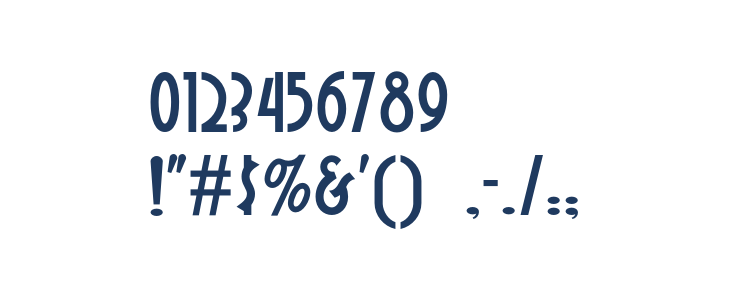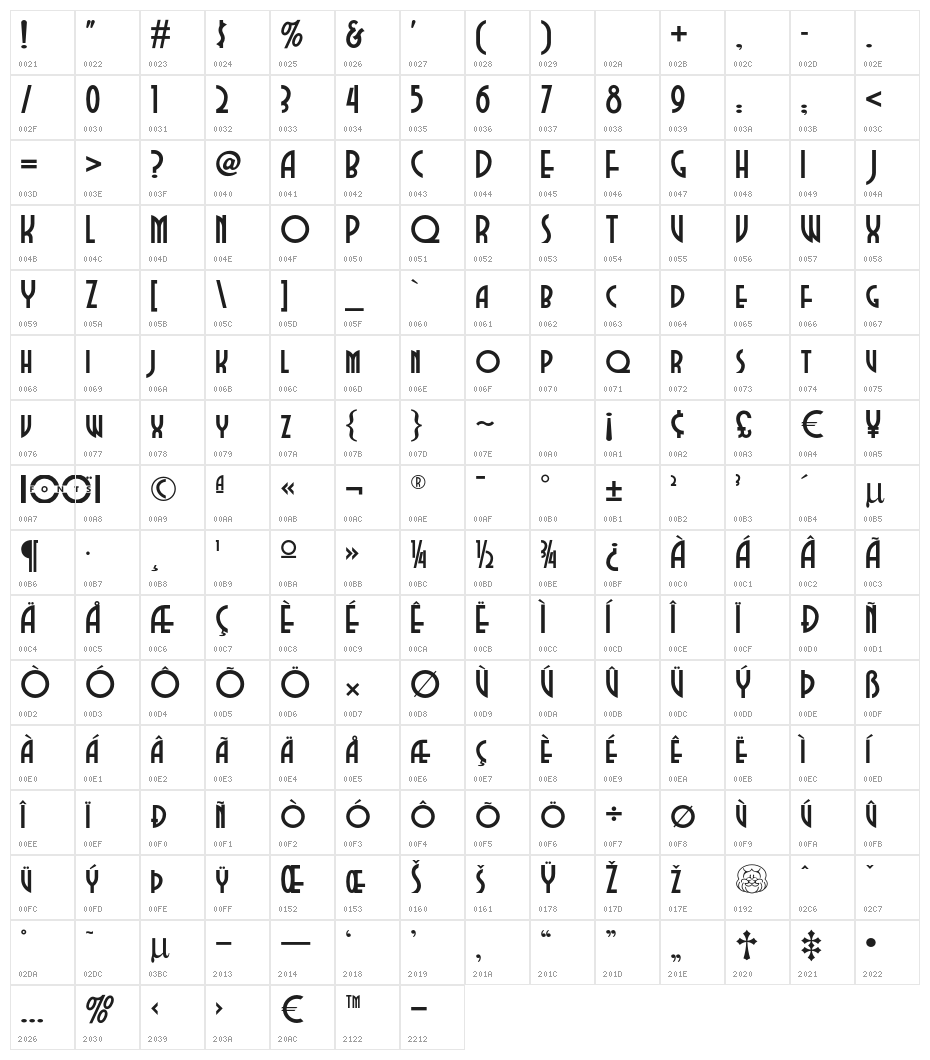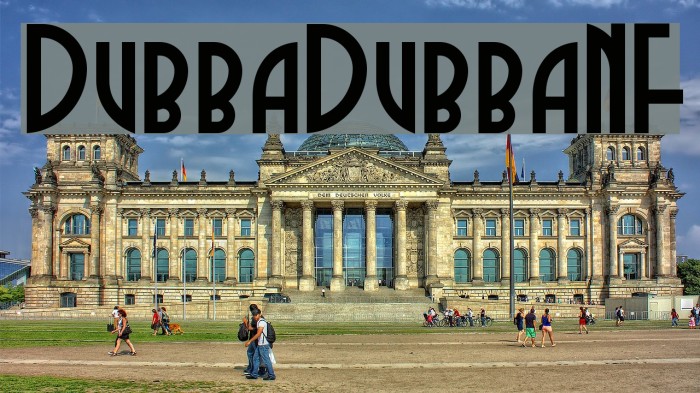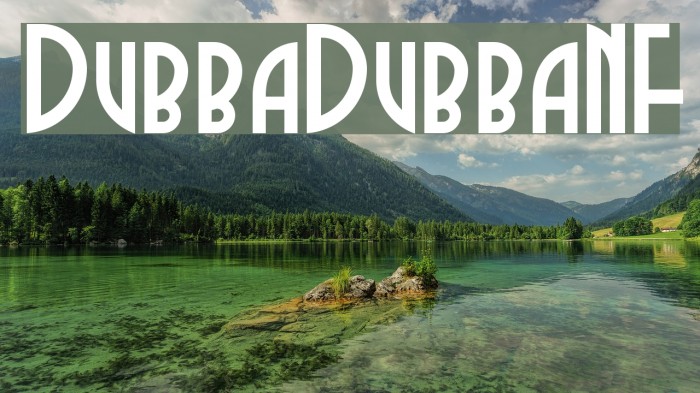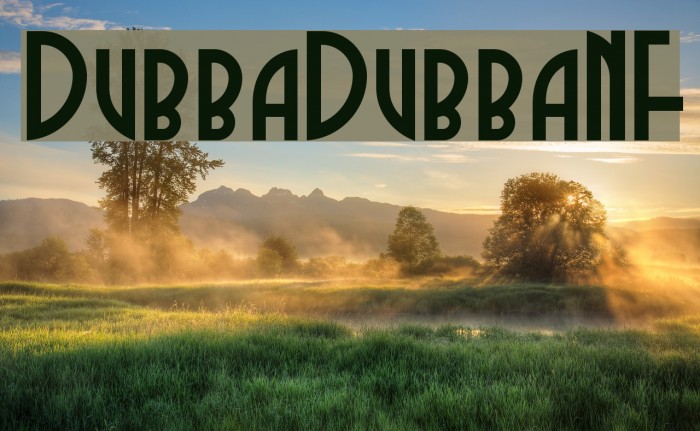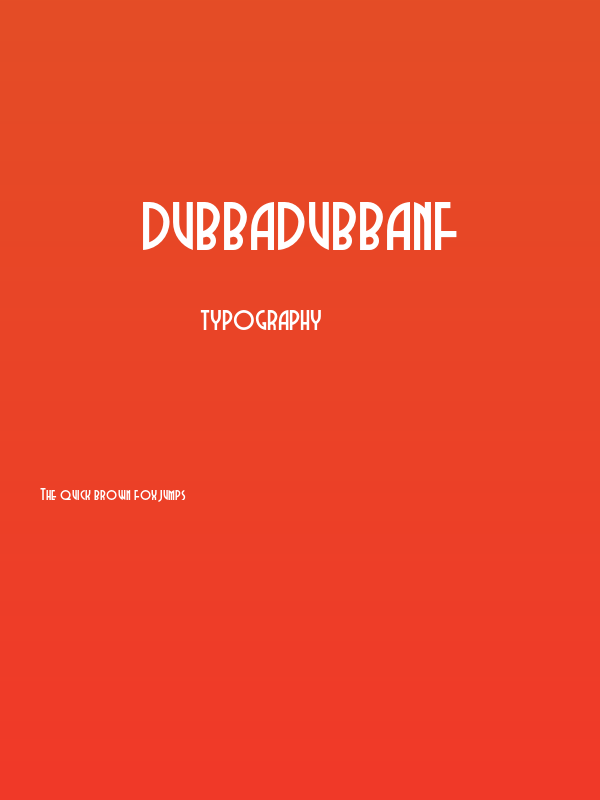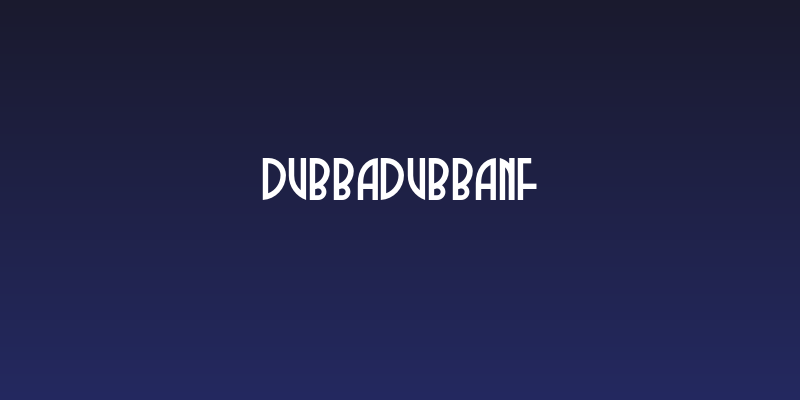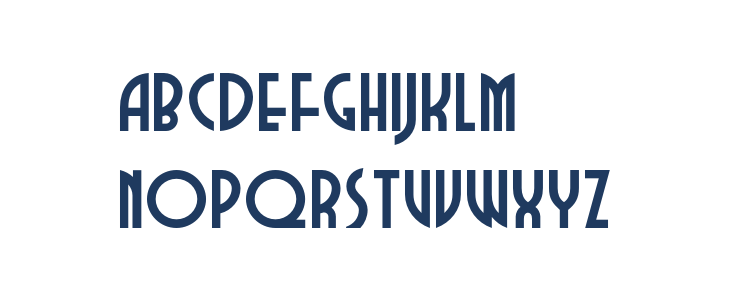
DubbaDubbaNF Font
✎ Art Deco
| Progetti proposti | This font is perfect for branding projects, vintage-themed posters, and any design work that requires a bold, eye-catching typeface. It can also be used in editorial design for magazine covers or feature spreads. |